今年も硬筆展の季節がやってきました。
教室では、一人ひとりが目標を持って、文字の形や大きさ、中心のそろえ方、とめ・はね・はらいまで、ていねいに練習を重ねてきました。
はじめは思うように書けなかったところも、くり返し取り組むうちに少しずつ整い、どの作品にもそれぞれの成長が感じられます。
今回は、そんな練習の積み重ねが伝わる作品を、ウェブギャラリーとしてご紹介いたします。
子どもたちが一文字一文字に向き合いながら頑張った様子を、どうぞごゆっくりご覧ください。
月曜日 4年生
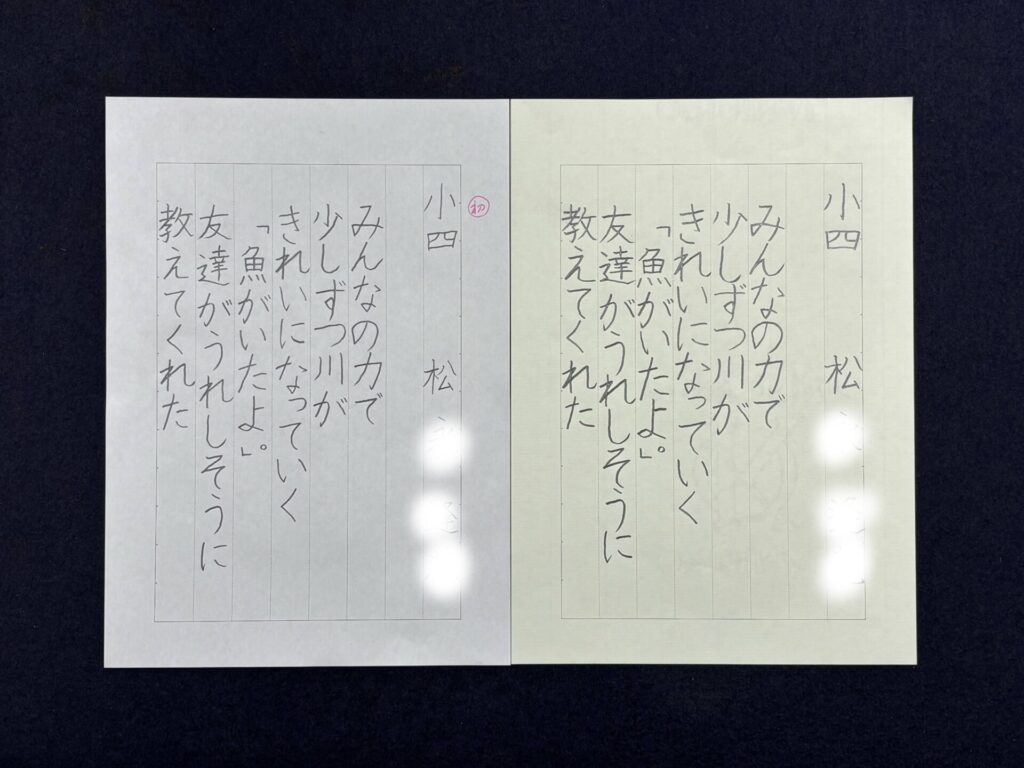
最初に比べると文字の形がより整い、大きく、まとまりが出ました。特に、行の中心がそろい、縦書きの流れがすっきりと美しく見えるようになりました。ていねいに書こうとする意識が最後の作品によく表れています。
月曜日 5年生
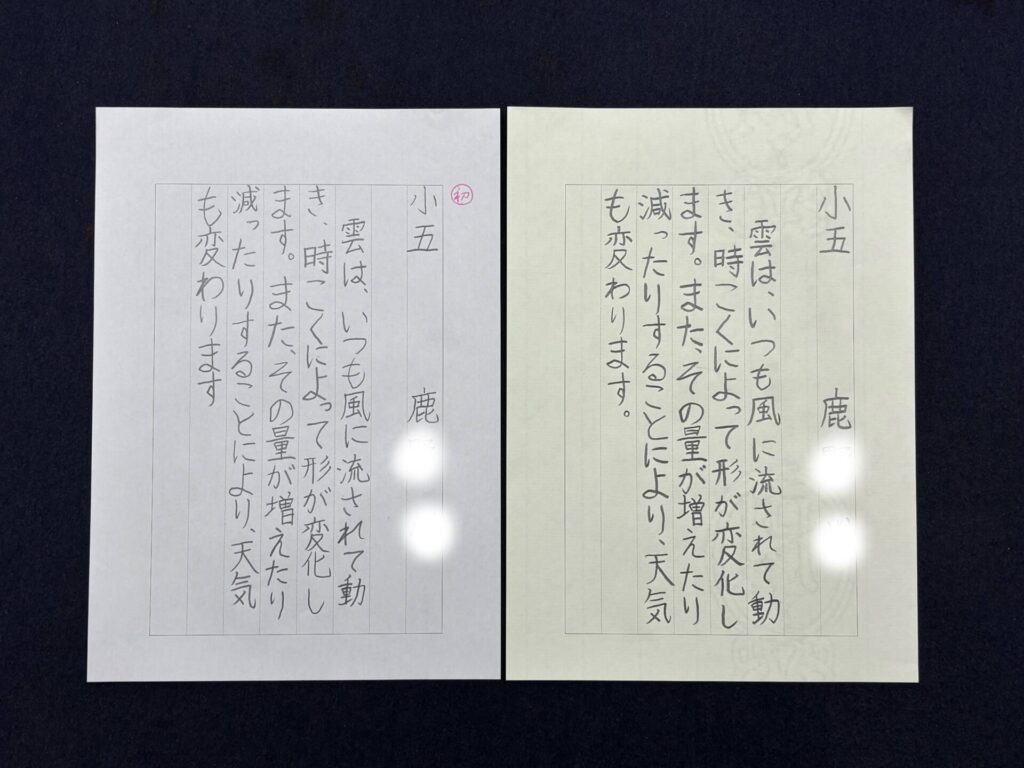
線の濃さや太さに安定感が出て、全体がぐっと引き締まりました。漢字を大きく、ひらがなをやや小さめに書く意識も感じられ、文字の組み立てがより美しくなりました。一文字一文字をていねいに整えながら書けるようになりました。
月曜日 4年生
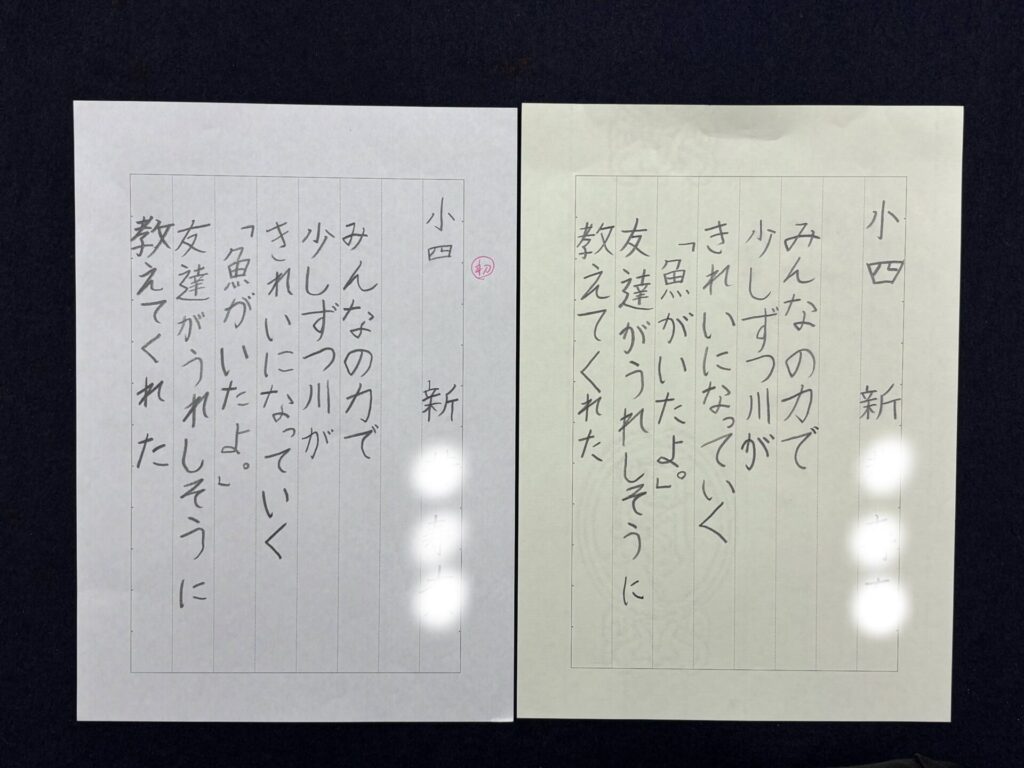
仕上げの作品は線の落ち着きが増し、字間や行の流れも整って全体がすっきりまとまりました。「小四」名前がが立派に書けるようになりました。ていねいに書こうとする意識がしっかり表れていて、練習を重ねた成果がよく伝わる作品です。
月曜日 3年生
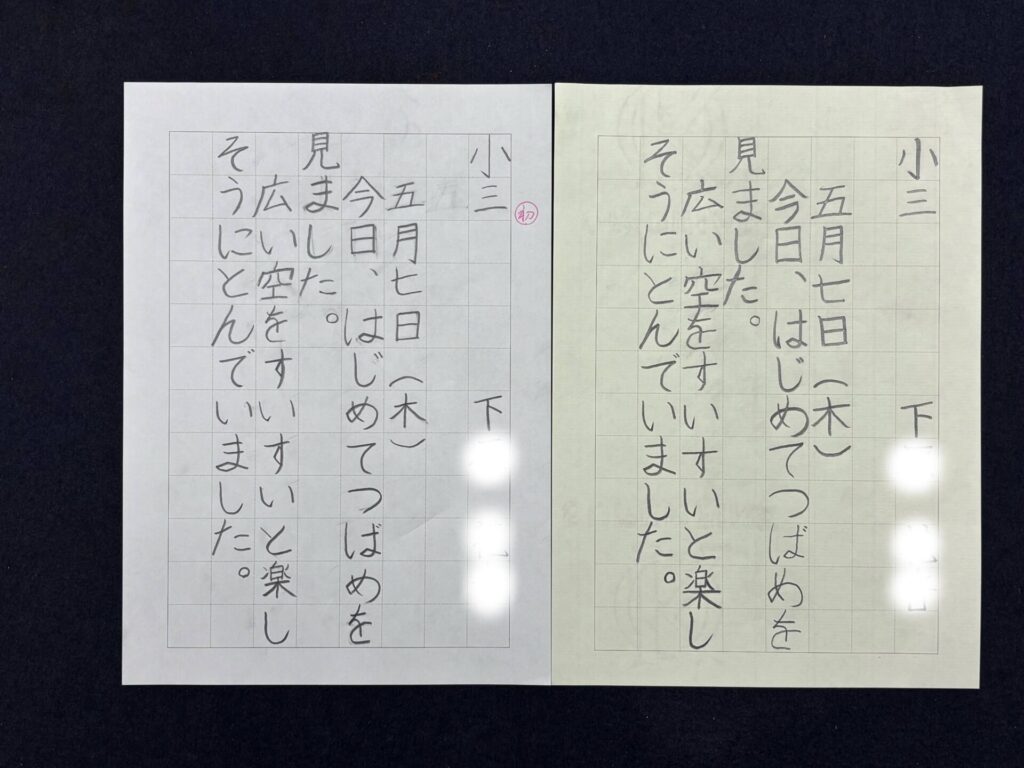
仕上げでは、文字を大きく、字の形も美しく整えて書けるようになりました。特に名前をたくさん練習してその成果が表れた作品です。明るく素直な印象の作品に仕上がっています。
月曜日 5年生
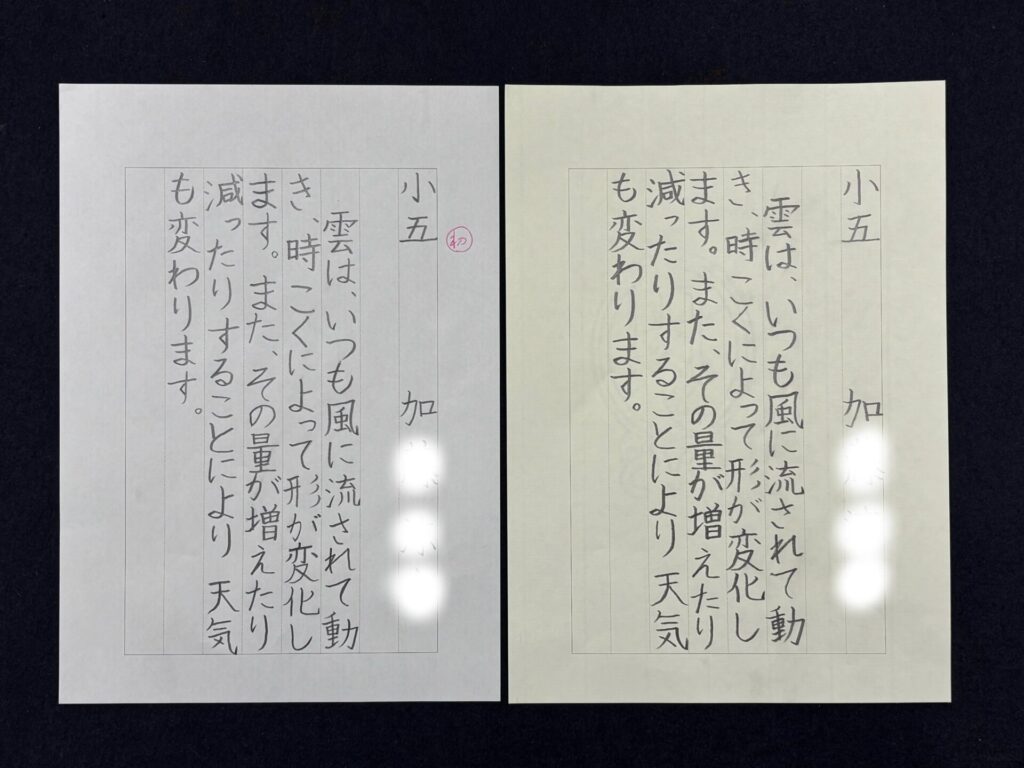
最初の作品と比べると線がしっかり書け、濃く、文字の形もぐんと整いました。漢字を大きく、ひらがなをやや小さめに書く意識が感じられ、文章全体が見やすくまとまっています。名前もたくさん練習して、整えて書けるようになりました。
月曜日 5年生
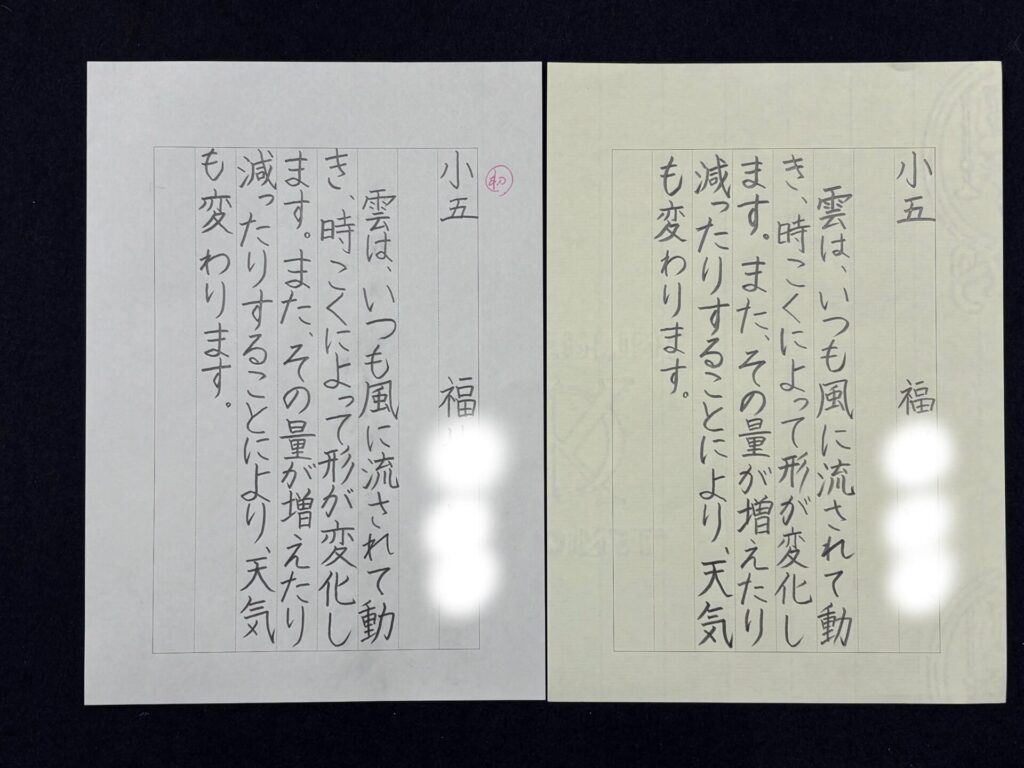
一画一画がぐっと力強く、ブレのない安定した線で書けています。特に「雲」や「風」の漢字がとても美しく整い、文字から自信が伝わってきます。漢字とひらがなの大きさのバランスもよく、最後まで集中して丁寧に書き上げることができました。
月曜日 6年生
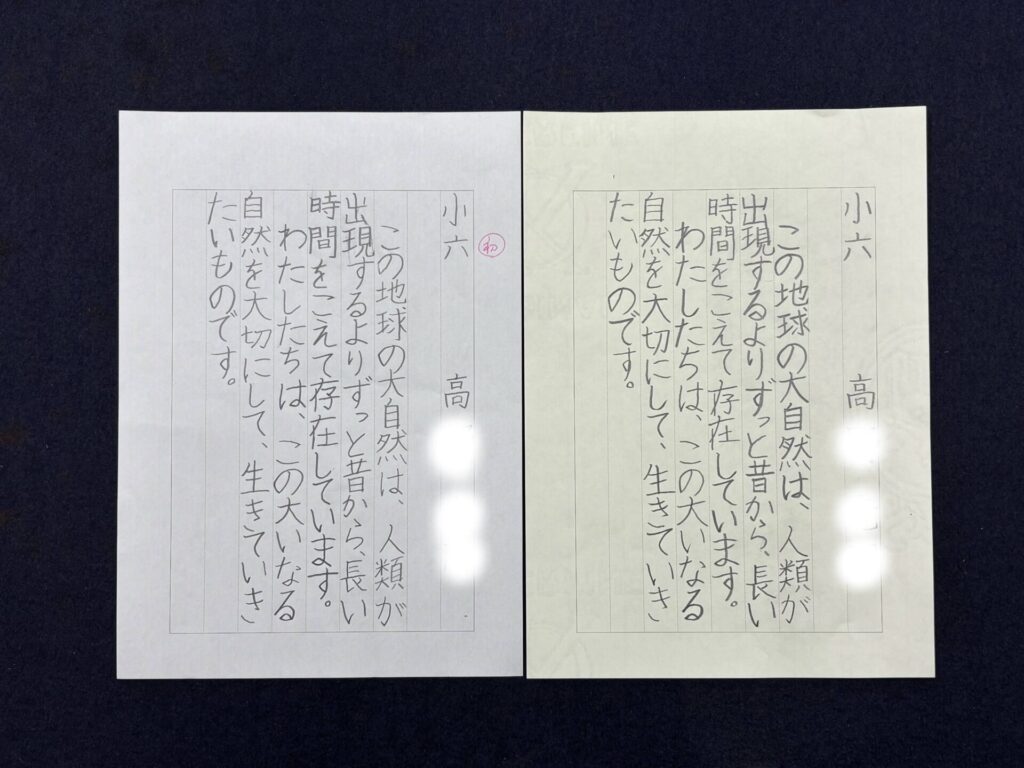
線の力強さが伝わる作品になりました。字間や行の中心もそろい、全体にすっきりとした流れが生まれています。最後まで丁寧に書こうとする気持ちが伝わる、落ち着いた仕上がりです。
月曜日 6年生
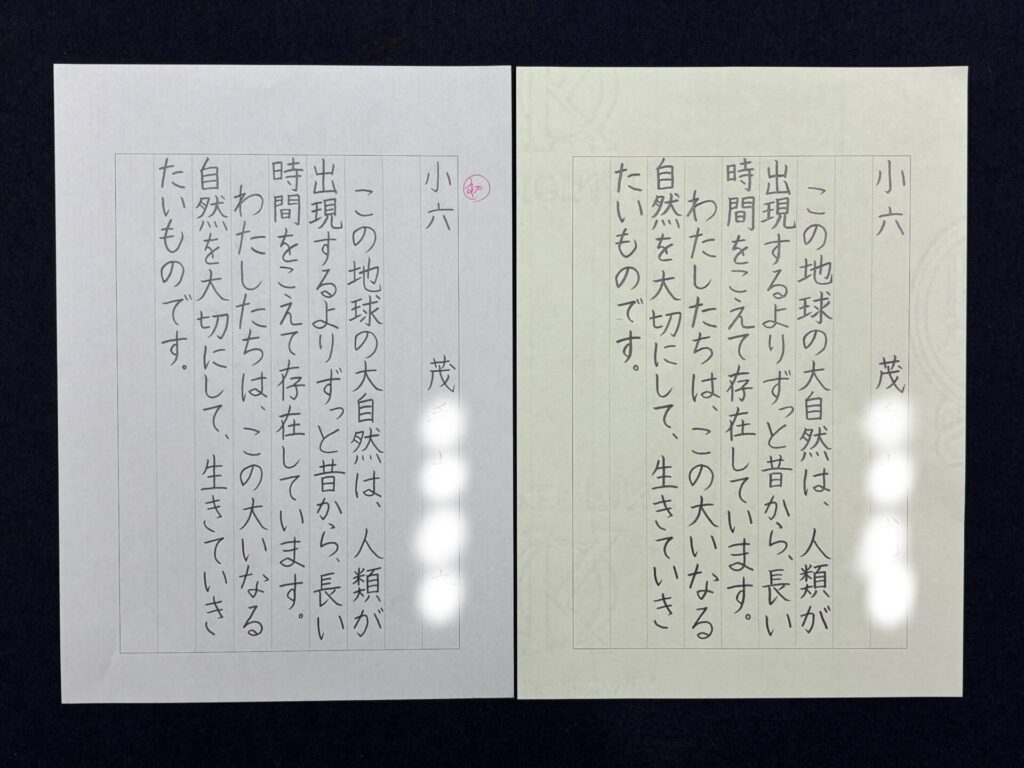
文字の大きさがよくそろい、濃く、全体がすっきりと見やすくなりました。とても素直な気持ちが伝わる字です。線にも安定感が出て、字間や余白の取り方まで整った、落ち着きのある一枚です。
今回ご紹介したのは、月曜日クラスの硬筆展練習作品です。どの作品にも、それぞれの頑張りや成長のあとがしっかりと感じられました。これからも、一文字一文字を大切にしながら、楽しく練習を重ねていきたいと思います。